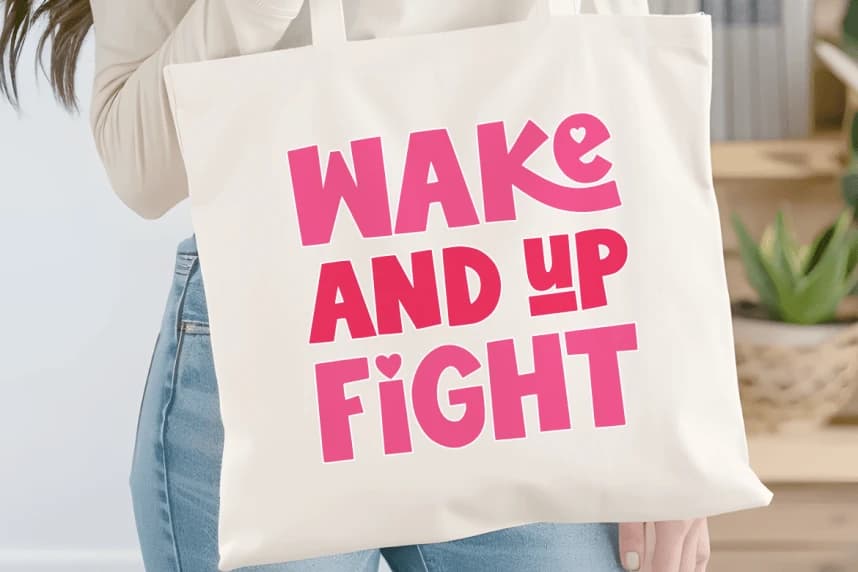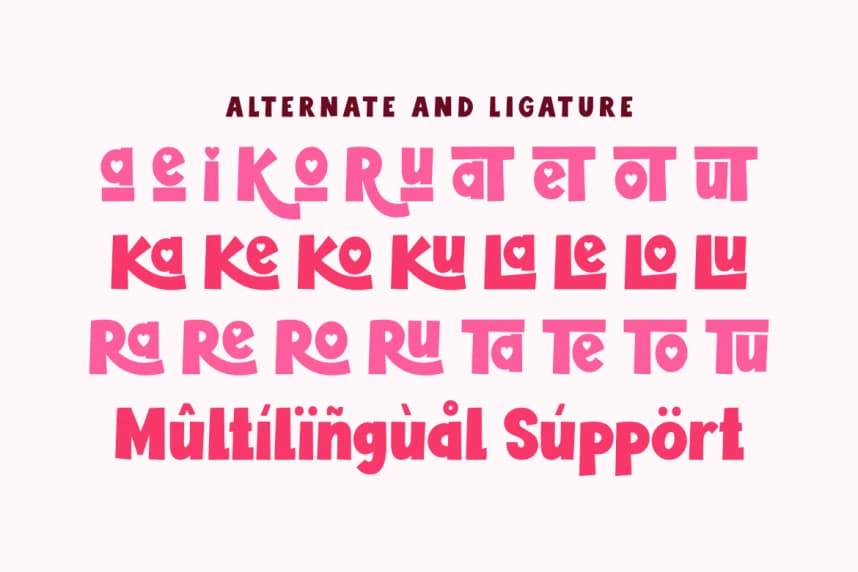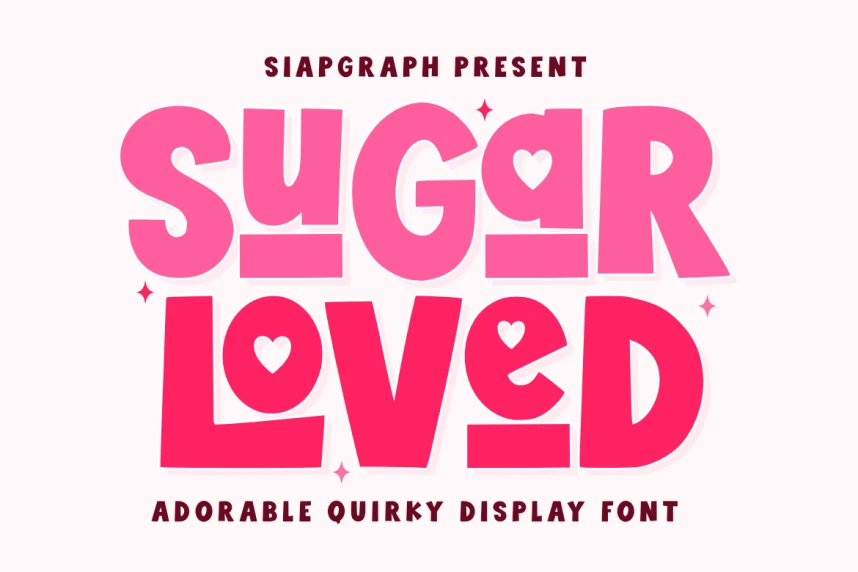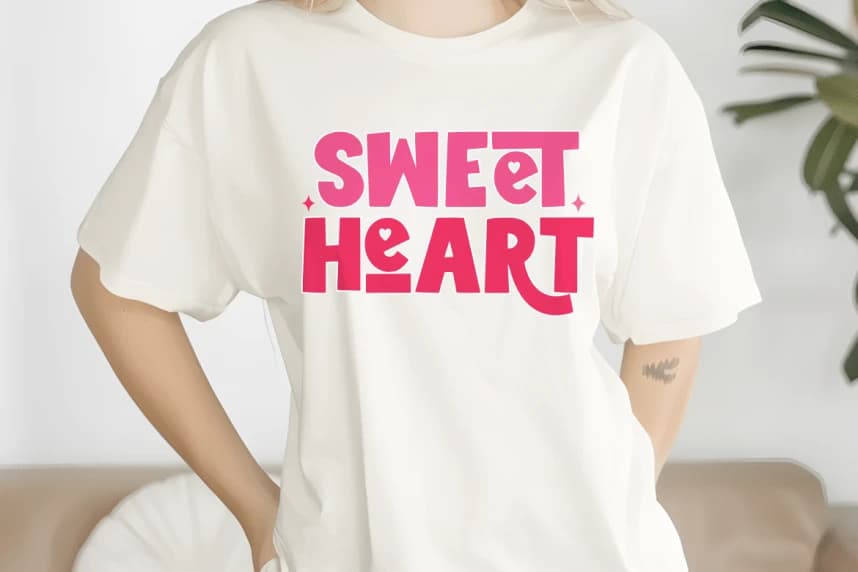
Sugar loved Font, renkli şekerlerin tatlılığından ve elden çizilmiş romantik doodle'ların oyuncu ruhundan ilham alan sevimli ve özgün bir display fontudur. Bu yazı tipi, kalın ve hacimli çizgilere sahip olup, karakterlere ustaca entegre edilmiş neşeli kalp vurguları ile büyülü ve sevgi dolu bir hava
Sugar loved Font, renkli şekerlerin tatlılığından ve el çizimi romantik doodle'ların oyun ruhundan ilham alan sevimli ve tuhaf bir gösteri yazı tipidir. Bu yazı tipi, karakterlere zekice entegre edilmiş sevimli kalp detaylarıyla birlikte kalın, iri çizgilere sahiptir ve masalsı, sevgi dolu bir atmosfer yaratır.